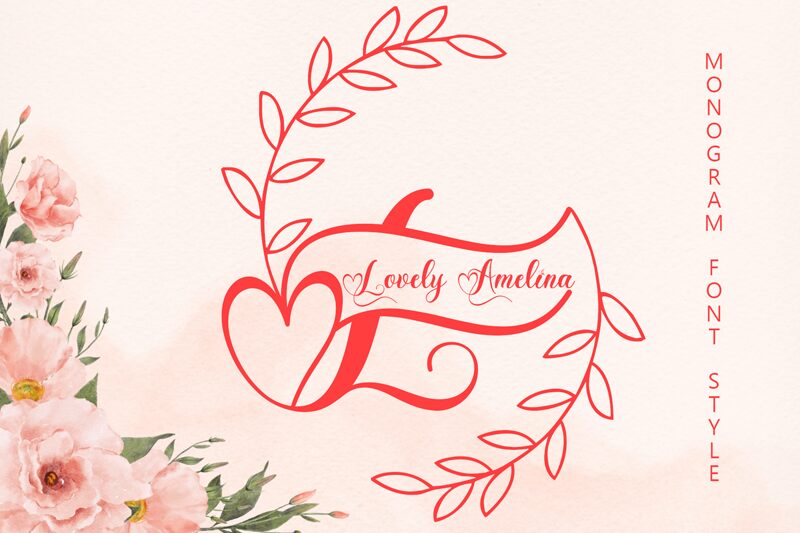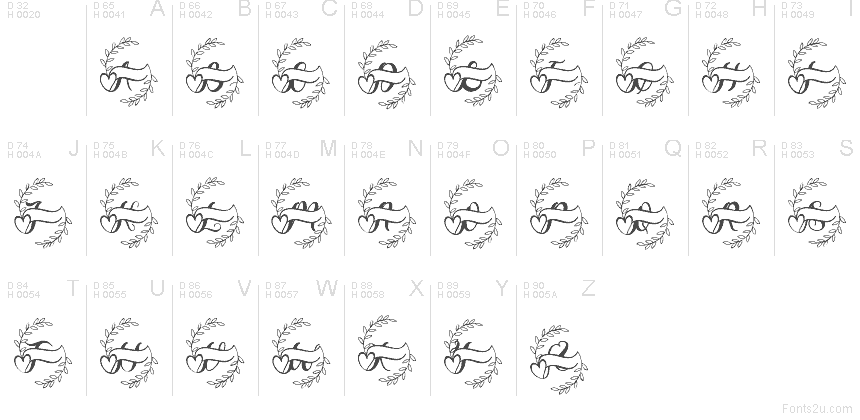
Lovely Amelina Monogram Demo
Lovely Amelina Monogram de Yoga Letter es una tipografía decorativa tipo display con un estilo de monograma floral, que combina una forma de corazón entrelazada, un banner curvo y finas ramas de hojas en un marco elegante. El trazo luce un estilo dibujado a mano y ligero, con motivos vegetales que envuelven el espacio central sin saturarlo.
Esta fuente gratuita funciona de maravilla en invitaciones de boda, tarjetas de nombre, logotipos, empaques de boutique y etiquetas de regalo donde se busca un monograma con un borde ornamental suave. Lovely Amelina Monogram Demo también es perfecta para detalles en redes sociales, etiquetas y papelería, ya que el arco de hojas y el centro en forma de corazón le dan a cada diseño un acabado personal y artesanal.